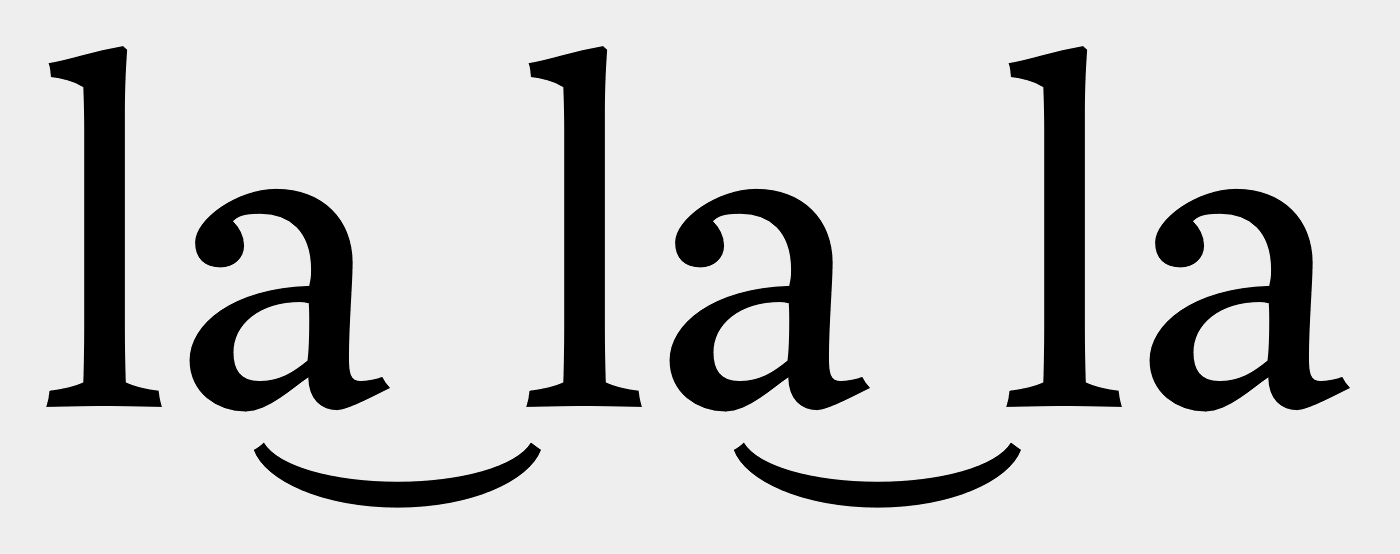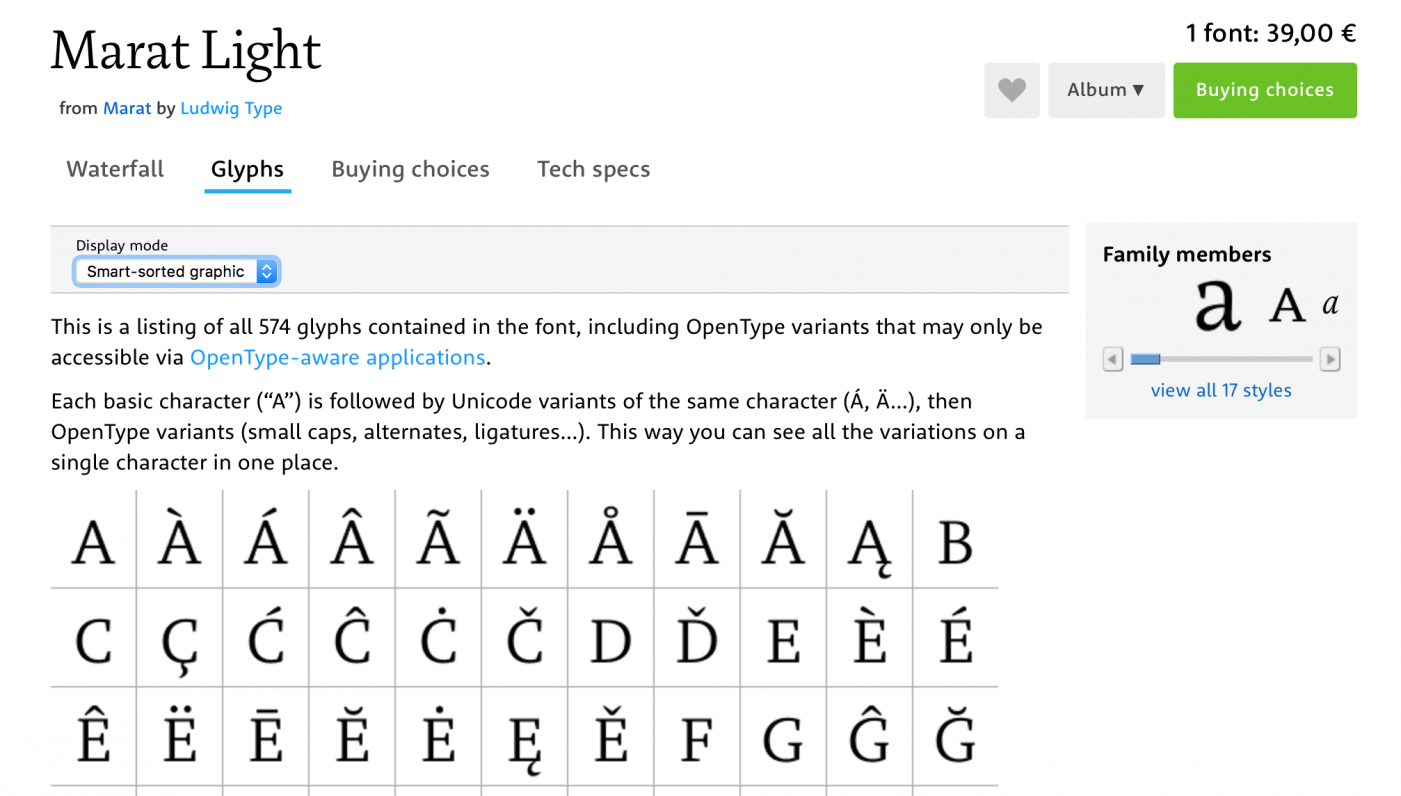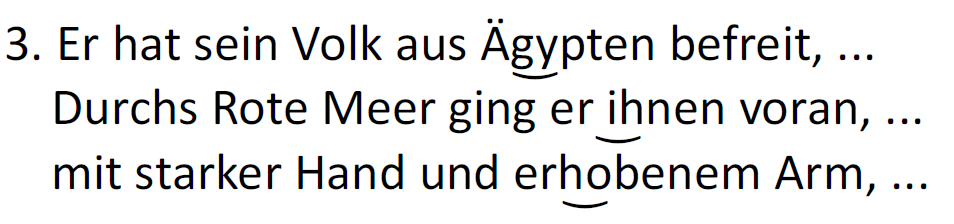
Schriftart für Liedtexte eines Liederbuches gesucht
wir sind dabei ein Liederbuch zu erstellen, um dieses kommerziell zu vertreiben. Die Lieder erstellen wir mit dem Notensatzprogramm "Finale". Soweit ist alles gut. Wir sind uns nur nicht einig, welche Schriftart wir für die Liedtexte, Titel, Credits etc. verwenden. Prinzipiell wollen wir nur eine Schriftart für alles verwenden. Ob wir eine Serif - oder Sans-Schriftart verwenden, ist noch nicht ganz sicher. Die Schriftart kann ruhig Geld kosten. Das Schriftbild sollte nicht zu klein und gut lesbar sein. Eventuell so eine Schriftart wie im katholischen Gesangbuch, dem Neuen Gotteslob. Wer kennt solche Schriften?
Jetzt habe ich in diesem Forum bereits einige Hinweise gefunden. Auch habe bereits einige für kommerzielle Zwecke freie Schriftarten probiert. Nur haben die freien Schriftarten das Problem, dass nicht alle benötigten Glyphen vorhanden sind. So nutzen wir zum Beispiel das Unicode-Zeichen 035C. Das ist eben z.B. in der Gandhi-Sans oder Gandhi-Serif nicht implementiert, so dass es zu Satzfehlern kommt. Bisher haben wir alles mit Calibri erarbeitet und konnten all unsere typografischen Wünsche damit umsetzen. Wir sind auf der Suche nach einer alternativen Schriftart, die etwa die Glyphen von Calibri abdeckt.
Welche Schriftarten könnten für unsere Zwecke in Frage kommen?
Gibt es noch vergleichbare Schriftarten, wie "DTL Documenta", die eventuell etwas günstiger sind?
Gibt es eigentlich vor dem Kauf einer Schriftart auch die Möglichkeit herauszufinden, welche Bereiche des Unicodes in der Schriftart umgesetzt sind? Z.B. die diakritischen Zeichen. Es ist ja schön, dass die Schriftart gut aussieht. Aber wenn gewisse Glyphen nicht vorhanden sind, nützt uns das beste Schriftbild nichts.
Das ist mir bisher irgendwie entgangen. Was ich mal finde, ist etwa welche Sprachen enthalten sind. Meinst du das?
Die Zeichentabellen werden meist mit Glyphs ausgezeichnet. Oder Du schaust Dir die Schriftmuster-PDF an, die kannst Du auch ausdrucken und im Anwendungsbereich mal probelesen. Liederbücher assoziere ich immer mit beschissener Beleuchtung und schwachsichtigen Menschen...
Nein, schau mal hier, das meine ich (MyFonts, am Beispiel „Marat“):
Nur sehe ich z.B. an der Marat Light, dass auch hier nicht alle benötigten Glyphen vorhanden sind. Mir geht es insbesondere um die diakritischen Zeichen, wie dem Unicode-Zeichen U+035C. Umgekehrte Frage: In welchen Schriftarten ist der Unicode relativ ganzheitlich umgesetzt worden? Kennt Ihr konkret Schriften, ohne das ich jetzt alle Schriften durchsuchen muss? Z.B. GNU FreeFonts FreeSerif und FreeSans sind quasi vollständig. Aber da ist das Schriftbild nicht besonders.
Wie auf der Webseite steht, ist die Liste nicht ganz vollständig. Es gibt jedoch viele Hinweise, wo ich gezielter suchen kann. Eine vollständige Liste wird es aber bestimmt nicht geben, besonders von den kommerziellen Schriftarten.
Bastel Dir eine Kurze Sequenz aller von Dir benötigter Sonderzeichen und kopier die bei Myfonts in die Schriftvorschau ("Your Text") und dann such in Deiner gewünschten Kategorie. Dann kannst Du sofort sehen, ob die Zeichen vorrätig sind oder nicht.
Die Marat Light ist aber schön! Musste dabei irgendwie spontan an die Swift denken (wahrscheinlich wegen dem coolen Tropfen z.B. beim kleinen a)
@haslingerDesign Schönheit ist das Eine, der Zweck das Andere. Wir brauchen nun mal ganz bestimmte Sonderzeichen, die im Standard Encoding nicht enthalten sind. Leider fallen dadurch fast alle Standardschriftarten raus.
Im Zusammenhang mit der "DTL Documenta" habe ich Kontakt mit der URW Type Foundry GmbH aufgenommen. Sie vertreiben diese Schriftart exklusiv für Deutschland. Allerdings würde die "DTL Documenta" für Deutschland auch nur mit dem Standard Encoding angeboten werden können. Das Zeichen U+035C ist damit nicht enthalten und darf auch nicht eingefügt werden, da die Rechte bei DTL Holland liegen. URW hat uns jedoch angeboten Ihre Schriftarten mit den Glyphen zu ergänzen, die wir speziell benötigen. Gegen einen bestimmten Aufpreis natürlich. Wir würde also eine eigene Schriftart generieren. Dass das möglich ist, hatte ich gar nicht auf dem Schirm. Wir werden aber darüber nachdenken.
Nur wenn 6 Verse vorhanden sind, lassen sich nicht alle unter die Noten pressen.
Vielleicht wäre es eine Alternative, die Silben über mehrere Noten hinweg einfach mit einem Unterstrich zu verbinden?
Bsp.: er_ho_benen Arm (OK, sieht vielleicht wirklich nicht so schön aus)
Ich kenne das Gotteslob jetzt auch nicht im Detail, aber ich kann mir nicht vorstellen, dass dort das von die gewünschte U+035C für diese Zwecke verwendet wird.